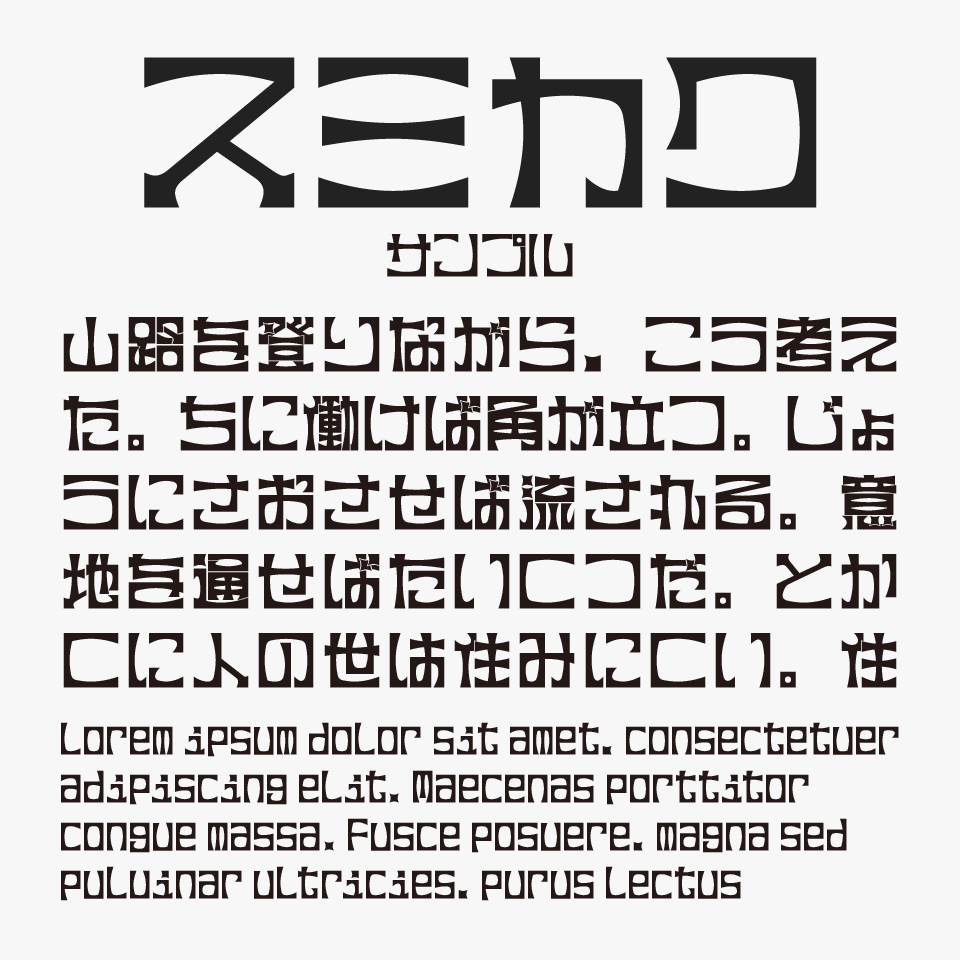
スミカクフォントは、正方形をベースに、隅付き括弧(【 】)を彷彿とさせるモチーフを取り入れられたデザインフォントです。
漢字・ひらがな・カタカナのいずれも、この「角をえぐる」デザイン処理が一貫して施されており、統一感も高く、見慣れた文字がどこか暗号めいて見えてくるのが面白いフォントです。
ゲームのタイトルロゴや格闘技・スポーツ系のビジュアル、インダストリアルなデザインなど、硬派でエッジの効いた世界観にぴったりなデザインフォントです。
スミカク
ひらがな○
カタカナ○
漢字○(教育漢字1,006文字)